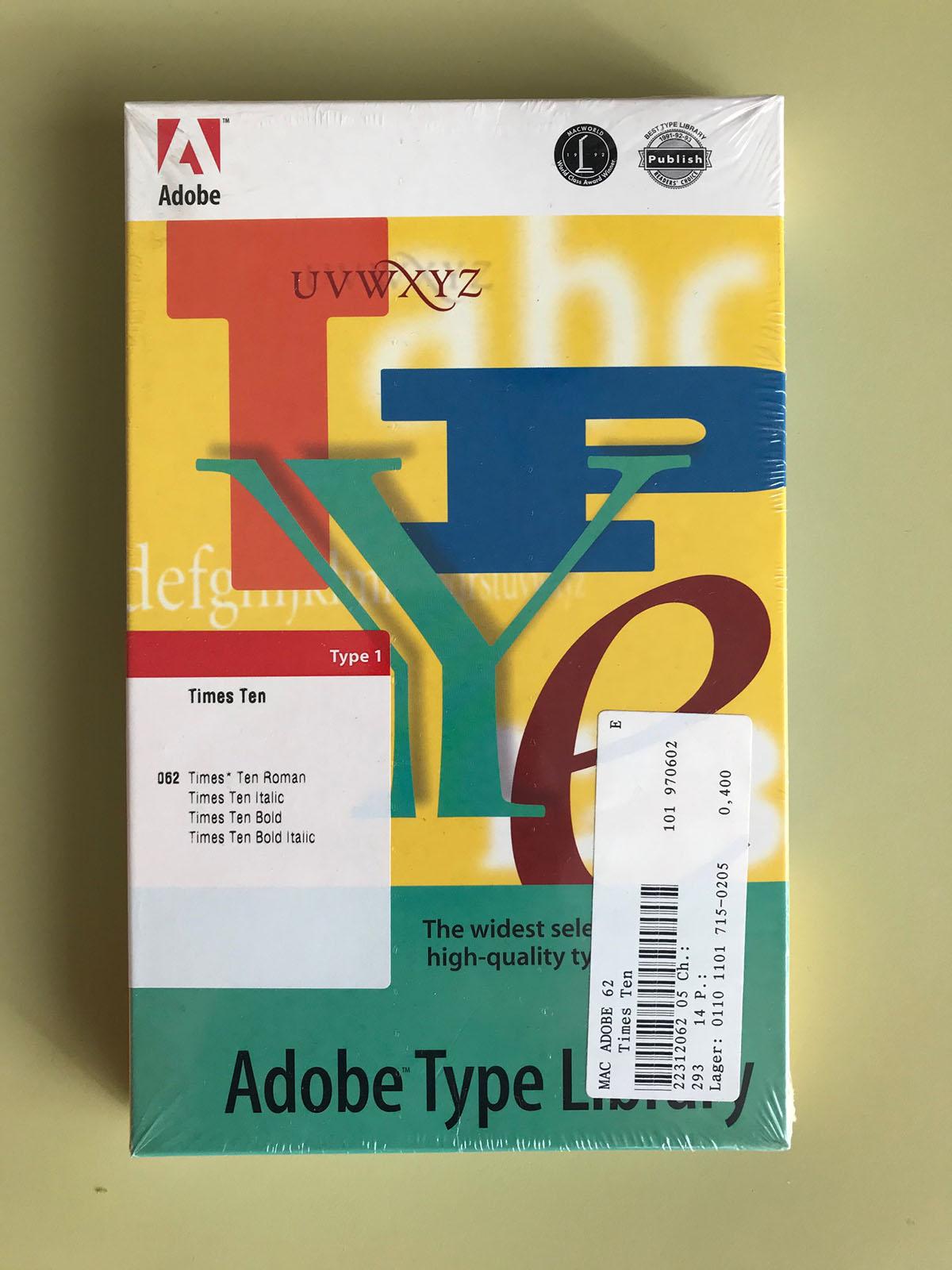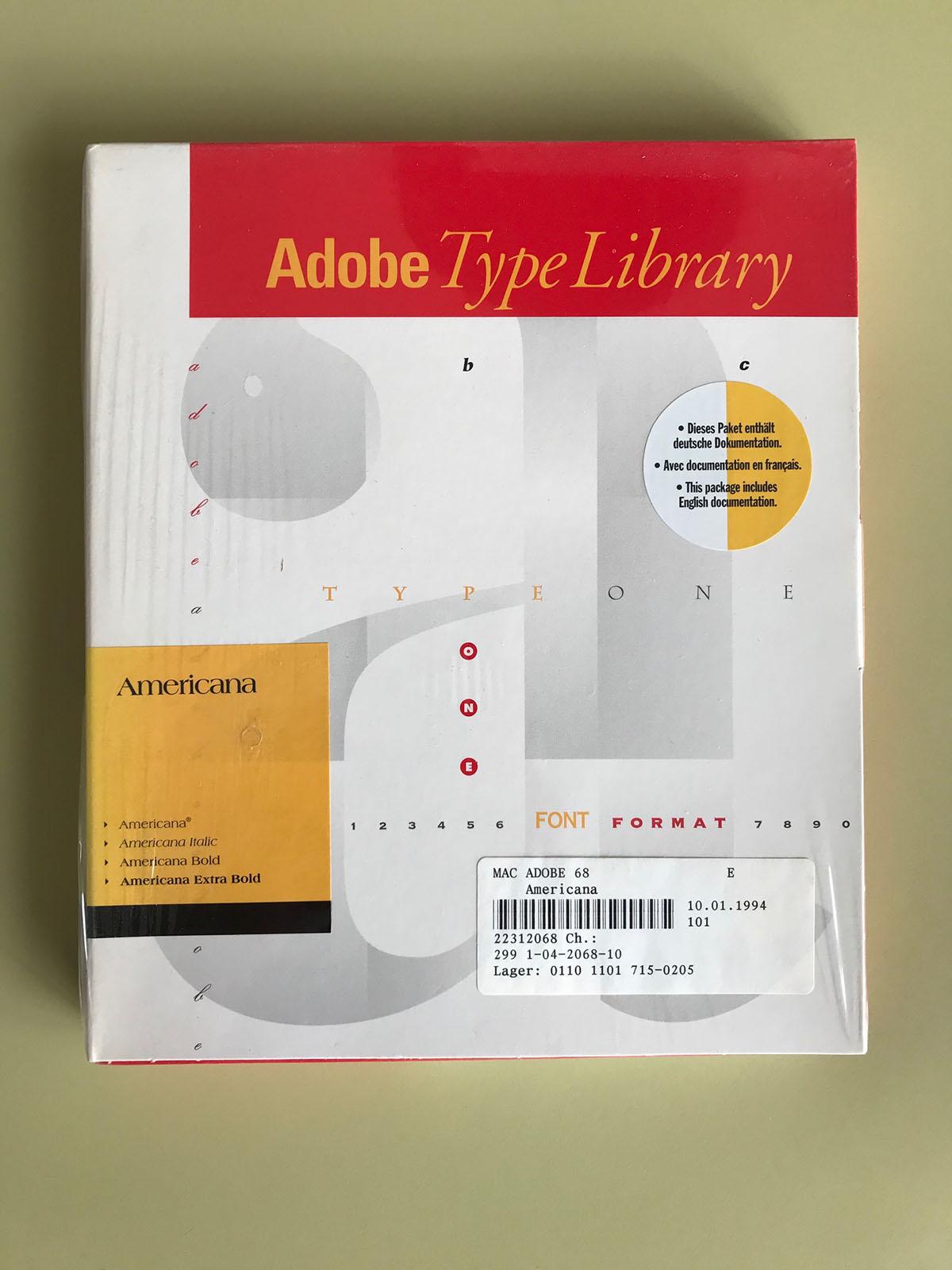
Da die größere Tochter sich gerade mit Zahlen und Buchstaben beschäftigt, hab ich ein illustriertes Alphabet erworben und heute endlich in einen Rahmen gesteckt.
hahaha, und ich dachte du hast das poster selbst gemacht, weil ich statt "erworben" "entwurfen" gelesen habe 😄
Nein, keineswegs, die treiben den Sexismus bis zum Exzess und loten aus, wie sie die Heuchelei us-amerikanischer Prüderie am krassesten bloßstellen können.
Wo arbeitest Du denn?
Tante Edith wunderte sich über einen nicht-bloodhound-gang-jedoch-clean-version-sicheren Arbeitsplatz
Das ist doch auf maximale Konfusion ausgelegt ...
C = Cue = Q
D = Double-u = W
E = Eye = I
Q = Queue = Cue ?
S = Sea = C
W = Why = Y
Y = You = U
Das soll ja auch ein Scherz-Alphabet sein :huhu:
Leider nein. :-(
Genau 🙂
Die Clarendon war meine erste Schriftlizenz. Vom Grabbeltisch bei Gravis für 15 Mark … :rockon:
Warum ich die Clarendon gleich zweimal erworben habe weiß ich ehrlich gesagt nicht mehr ... :-? Muss ich dann wohl mal wieder verstärkt einsetzen. :hammer:
Warum eine Rosette bei "O" abgebildet ist, erschließt sich mir aber nicht … :-|
Yepp. Richtig subversiv.
Damit wären für mich ganze Straßenzüge ansprechender, weil individueller scheisse beschildert 😄
Ist hier irgendwem die Griffelkunst ein Begriff? Seit ein paar Jahr bin ich nun Mitglied und unterstütze das Team vor Ort bei den Wahl- und Sonderausstellungen. Jetzt möchte ich euch unbedingt ein Blatt zeigen, das im Herbst letzten Jahres zu Wahl stand und ich nun endlich bekommen habe. Das passt hier in so vielen Themen rein …
Es handelt sich um einen zweifarbigen Holzschnitt in ca. 60x80cm. Im Treppenhaus, wo es jetzt hängt kann man leider schwer fotografieren.
Aber ja ... ich hatte als Student das Vergnügen, mal die Privatsammlungen des Herrn Schack zu besichtigen, da zwei meiner Profs mit ihm befreundet bzw. bekannt waren. Und da gab es auch dann Griffelkunstgeschichten zum Besten ;-)
Davon hatte ich noch nie gehört. Habe mir gerade die betreffenden wiki-artikel reingezogen, bin aber genauso dumm als wie zuvor. Handelt es sich hier nun um einen Stil, oder um grafische Werke allgemein?
Nicht typografisch im engeren Sinne, aber vielleicht trotzdem interessant: so werden hierzulande die überall anzutreffenden, hölzernen Strommasten nummeriert. Ich stelle mir vor, daß sich die Fertigung der Metallziffern seit hundert Jahren nicht geändert hat.
Als ich in der Klapse war, hätte ich das in der Ergotherapie machen können. Aber ich hab lieber an meiner Handschrift und an kalligraphischen Schwüngen gearbeitet.